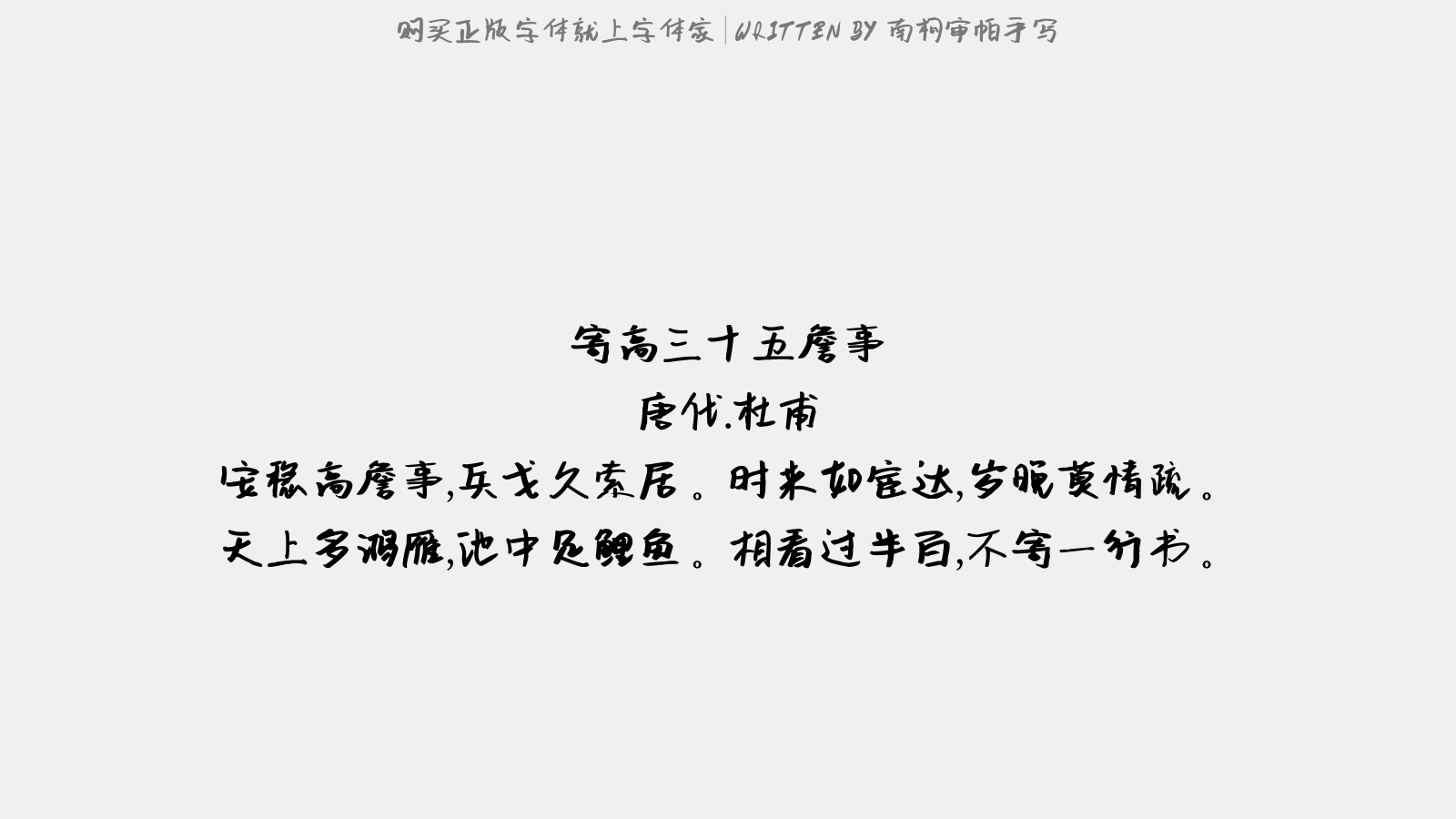
南构审帕手写
字体作者:南构字库
字体名称:南构审帕手写
字体字数:26个英文大小写字母及和阿拉伯数字和6763个汉字
字体家族:南构手写体系列
书体类型:书法类
南构审帕手写
南构审帕手写字体是一款独特的艺术字体,由南构字库出品,它的笔画偏粗,字形自然随性,给人一种放松、随意的感觉。它似乎是用马克笔或软笔墨汁书写的,每个文字都具有自己独特的韵味。
这种字体大气醒目,非常适合用于各种场合的设计,无论是书籍装帧、平面设计、广告设计还是字体设计等等,都能够体现出极高的艺术价值和实用价值。对于喜爱书法和绘画的人来说,南构审帕手写字体不仅是一种字体,更是一种艺术和审美的追求。
南构审帕手写 - 宴清都
南构审帕手写 - 寄高三十五詹事
南构审帕手写 - 题万道人禅房
南构审帕手写 - 大写字母/小写字母/数字